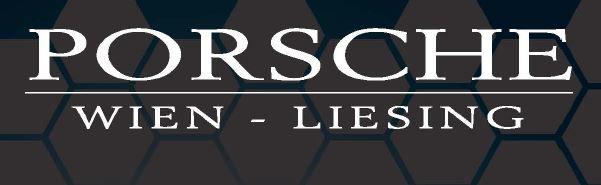
Wie heißt diese Schrift? (Porsche Wien)
Kann mir bitte jemand sagen, was für eine Schrift das ist?
Da könnte die Berling Pate gestanden haben … in die Breite gezogen: